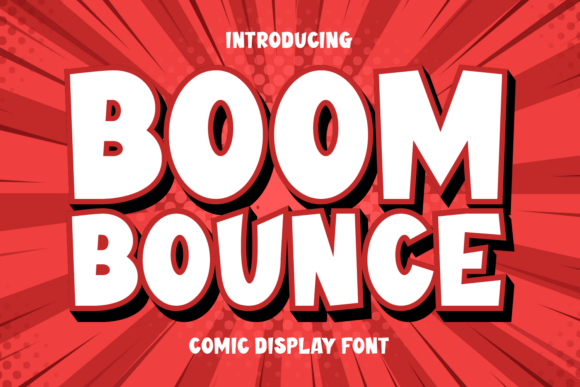
Boom Bounce
Boom Bounce: A Jogo de Letras Criativas e Encantadoras
** **O que é Boom Bounce?
**Boom Bounce é uma fonte de exibição incrível que conquista com seu toque cómico contemporâneo e charme de criança amigável. Criado especialmente como uma ferramenta para criar títulos inspiradores e posts de mídia social envolventes, sua simplicidade torna-o perfeito para projetos escolares e mídia impressa.
**Características e Benefícios
**- Design Cômico**: Boom Bounce captura a nostalgia dos heróis cómicos amados, adornado com accents brincantes e lembranças de desenhos de papel de parede vintage.
- Transforme seus Projetos**: Com seus elementos cústicos naturais, Boom Bounce transforma a sua visão em uma obra de arte visual, seja em capas de livros, branding, roupas de vestuário, cartões de parabéns ou criações sazonais.
- Leitura Suave**: A leitura em Boom Bounce é suave e acessível, tornando-o uma escolha perfeita para cartões de parabéns, cartões de agradecimento ou outros materiais de comunicação.
Por que Escolher Boom Bounce?
**Boom Bounce é uma fonte versátil e charmosa que combina autenticidade e tendência. Suas características de design, como a presença de accents cústicos e a simplicidade, tornam-no uma escolha perfeita para muitos projetos. Além disso, sua multiliníngua torna-o uma ferramenta valiosa para a conectividade global.
**Conclusão
**Boom Bounce é uma fonte incrível que tem o poder de transformar seus projetos em obra de arte visual. Com sua combinação de design cómico, simplicidade e multiliníngua, é uma escolha perfeita para muitos projetos. Não perca a oportunidade de experimentar Boom Bounce e descubra como pode tornar sua visão em realidade!